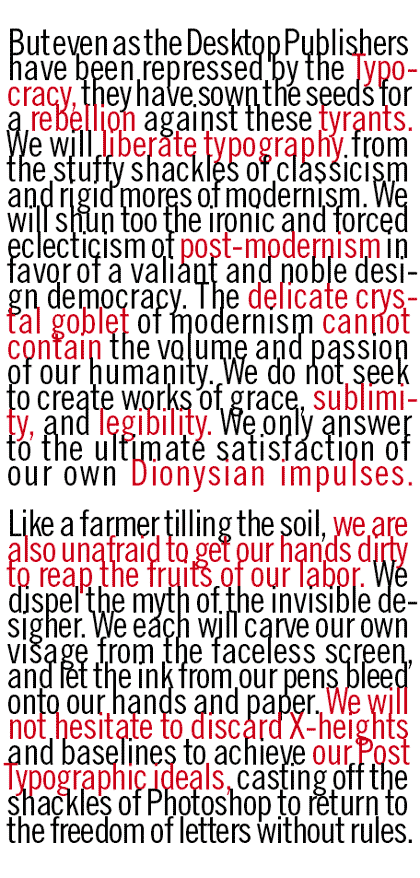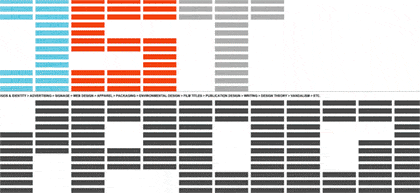
Post Typography | vous avez tué la typographie, vive la rebellion!
Au détour d’un voyage qui m’a fait visiter la Typography Planet, petit tour de monde initiatique que chacun peut faire à condition d’avoir quelques clés, je découvre en fin d’après-midi le site de Post Typography créé et animé par Nolen Strals and Bruce Willen. J’y découvre tout ce que j’ai toujours aimé, la transgression, le DaDa moderne de deux graphic-designers en rupture de bans avec les conventions et les règles largement diffusées par tous les manuels de typographie qui fleurissent à chaque coin de rayonnage dans les bonnes librairies graphiques. Difficile de ne pas évoquer les travaux de Catherine Zask ou de Pierre di Sciulio tant le mode opératoire dans les recherches et expérimentations est similaire. Déstructuration de l’espace graphique et typographique, mise en scène des punctums qui vont ‘attiser’ l’œil du spectateur etc. Je vous laisse découvrir tranquillement cette œuvre assez gigantesque qui ne touche pas, bien évidemment, qu’à la seule mise en scène typographique, mais aussi aux logos, affiches, packaging, couvertures de livres etc.
Le Manifeste
Pour ce qui est du Manifeste (extrait ci-dessous) publié par les deux créateurs on peut esquisser un sourire en se disant que nous autres européens n’avons pas attendu l’arrivée du Desktop Publishing pour partir en guerre contre les conventions et la ‘Typocracy’. Le mouvement DaDa a accompli un travail sournois et constant qui se révèle au grand jour dans les créations contemporaines. Il s’agit d’ailleurs autant d’une posture esthétique que politique.
Home page de Post Typography
Quelques travaux typographiques réalisées par le Studio situé à Baltimore sur la côte est des États Unis.
Le Manifeste ‘extrait’: